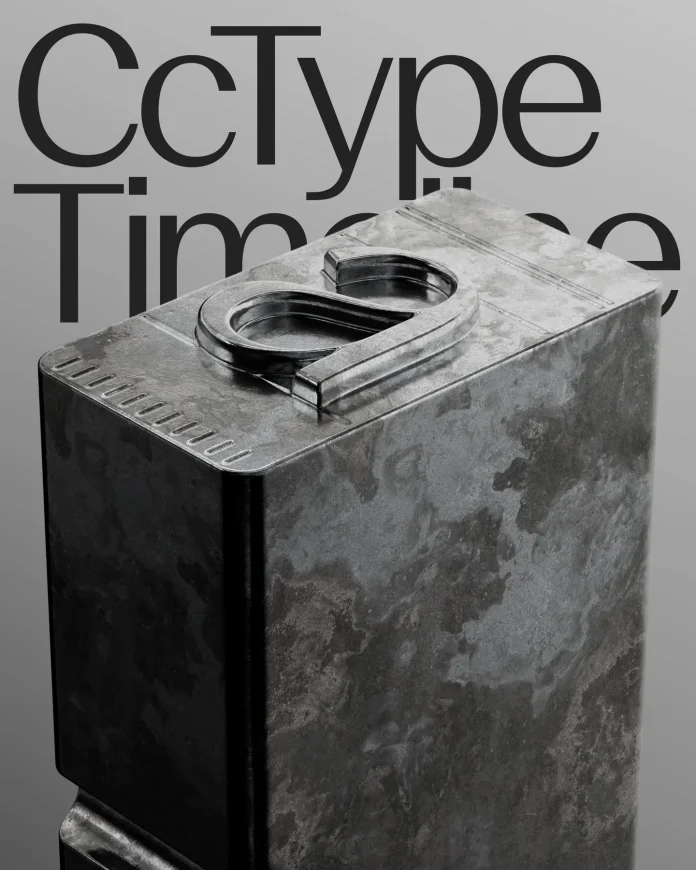
La bonne typographie est-elle devenue un luxe ?
Koto vient de lancer CcType avec une ambition affichée : proposer des caractères de qualité à des conditions suffisamment accessibles pour les indépendants et les petites structures. L’initiative arrive dans un paysage paradoxal. Les designers disposent d’un choix typographique immense, souvent gratuit ou compris dans leurs abonnements, tandis que certaines licences professionnelles restent complexes et coûteuses à déployer. Comment maintenir une création typographique exigeante sans la réserver aux projets les mieux dotés ?
Koto dessine des caractères depuis longtemps dans le cadre de ses projets d’identité. Avec CcType, le studio leur donne désormais une existence autonome. Sa première famille, CcTimeline, comprend plusieurs sous-familles, dix-huit styles et une version variable. Les styles sont proposés à partir de 60 livres, avec une licence calculée selon la taille de l’entreprise et couvrant les principaux usages de marque, du web aux applications. Le positionnement tarifaire compte, mais la simplicité de la licence joue probablement un rôle tout aussi important. Jowey Roden, cofondateur de Koto, présente CcType comme une manière d’élargir l’accès au savoir-faire typographique développé par le studio. L’initiative rejoint ainsi une question qui traverse depuis plusieurs années le dessin de caractères : que signifie encore rendre une bonne typographie accessible lorsque d’excellentes fontes sont déjà disponibles gratuitement ?
Une abondance qui change la perception de la valeur
La rareté typographique appartient largement au passé. Adobe Fonts donne accès à des milliers de familles dans l’abonnement Creative Cloud. Google Fonts a installé l’open source dans les habitudes de travail, jusqu’à accueillir des caractères initialement développés sur mesure pour des entreprises ou des institutions. Fontshare propose de son côté une importante sélection de familles utilisables gratuitement dans des projets personnels et commerciaux. Un étudiant, une association, une petite entreprise ou un designer indépendant peuvent aujourd’hui produire un projet avec des caractères d’excellente qualité sans consacrer de budget spécifique à leur acquisition.
Cette situation constitue un progrès considérable, tout en modifiant profondément la perception économique d’une fonte. Lorsqu’une bibliothèque entière est incluse dans un abonnement ou disponible gratuitement dans Figma, payer plusieurs centaines d’euros pour une autre famille demande une justification plus précise. La question se déplace alors vers la diversité. Certaines familles ouvertes ou gratuites deviennent omniprésentes et finissent par constituer un vocabulaire graphique commun. Inter, Roboto, Poppins ou certaines grotesques contemporaines apparaissent dans une quantité considérable d’identités et d’interfaces. Leur diffusion ne remet rien en cause de leur qualité ; elle montre simplement que l’accessibilité intervient directement dans les choix. Une fonte issue d’une fonderie indépendante permet souvent d’aller chercher ailleurs : un dessin moins familier, un contexte culturel différent, une couverture linguistique particulière, une voix capable de singulariser davantage un projet. Le prix contribue aussi au financement de cette diversité.
La difficulté économique du caractère tient en partie à sa nature numérique. Une fois terminé, le fichier peut être reproduit presque sans coût, alors que sa conception mobilise un travail considérable : dessin des glyphes, espacement, kerning, graisses, italiques, accents, caractères alternatifs, fonctions OpenType, couverture linguistique, tests, corrections, versions variables et maintenance. Une famille complète peut demander des mois, parfois plusieurs années de développement. Rien de cet investissement n’apparaît au moment où l’utilisateur installe le fichier en quelques secondes. Le modèle devient particulièrement délicat pour les petites fonderies. Une agence internationale comme Koto peut développer une activité typographique parallèlement à ses projets de branding ; un studio dont la vente de caractères constitue la principale source de revenus doit trouver dans ses licences de quoi financer le travail déjà accompli et celui qui suivra. L’accessibilité doit donc rester compatible avec une économie viable pour ceux qui produisent.
Les licences au cœur du problème
Le prix affiché d’une fonte ne permet pas toujours de connaître le coût réel de son utilisation. Desktop, web, application, réseaux sociaux, vidéo, packaging, ePub, publicité numérique : les licences peuvent se multiplier selon les supports. Certaines tarifications évoluent également avec le nombre de postes, les pages vues ou la taille de l’entreprise. Cette organisation répond à une logique compréhensible. Une fonte utilisée par un restaurant indépendant et la même famille déployée mondialement par une multinationale ne produisent pas la même valeur économique. Les fonderies cherchent donc à faire correspondre leur rémunération à l’ampleur de l’usage.
La complexité apparaît lorsque le designer doit anticiper toute la vie d’une identité dès sa conception. Une petite entreprise saisira facilement le coût d’un photographe ou d’un imprimeur ; expliquer qu’un caractère implique une licence différente pour son site, son application ou ses campagnes peut se révéler plus difficile, surtout lorsqu’une alternative gratuite existe à quelques clics. Plusieurs acteurs tentent aujourd’hui d’alléger cette friction. XYZ Type a simplifié certaines de ses licences autour de la taille de l’entreprise. CcType suit une logique voisine. La plateforme fonts.xyz propose elle aussi une licence couvrant de nombreux usages, avec une tarification indexée sur la taille de la structure et un modèle qui entend mieux rémunérer les fonderies participantes. La lisibilité du contrat commence ainsi à devenir un argument presque aussi important que le prix lui-même.
Cette évolution révèle un point souvent sous-estimé : une fonte gratuite possède elle aussi une économie. Google peut financer le développement d’un caractère parce que l’entreprise a intérêt à disposer d’un web riche, multilingue et techniquement performant. Une grande marque peut commander une famille puis choisir de la rendre open source. Une fonderie peut diffuser gratuitement une partie de son catalogue pour faire connaître le reste de son travail. Le prix payé au moment du téléchargement ne dit donc qu’une partie de l’histoire. L’open source joue par ailleurs un rôle culturel majeur en donnant accès à des familles ambitieuses à des créateurs dont les moyens économiques diffèrent fortement selon les territoires. Il facilite aussi le travail multilingue et élargit considérablement le niveau de qualité accessible aux projets les moins dotés.
Sélection de caractères NaN disponibles sur fonts.xyz, plateforme dédiée aux fonderies et designers typographiques indépendants. Crédit : NaN / fonts.xyz
Faire entrer la typographie dans le budget du projet
Reste une question très concrète : qui doit payer la licence ? Dans une identité de marque, le caractère choisi fait partie du système graphique au même titre que les principes photographiques, les illustrations ou les éléments développés sur mesure. Pourtant, son coût reste parfois absorbé par le studio ou découvert tardivement par le client. Certaines fonderies travaillent désormais directement sur cette articulation entre conception et achat. Elles permettent au designer de tester les caractères pendant la phase de recherche, puis de préparer ou transférer la licence correspondant aux besoins du client. Cette organisation replace la typographie parmi les coûts normaux d’une identité et évite qu’elle soit traitée comme une dépense secondaire ajoutée en fin de projet.